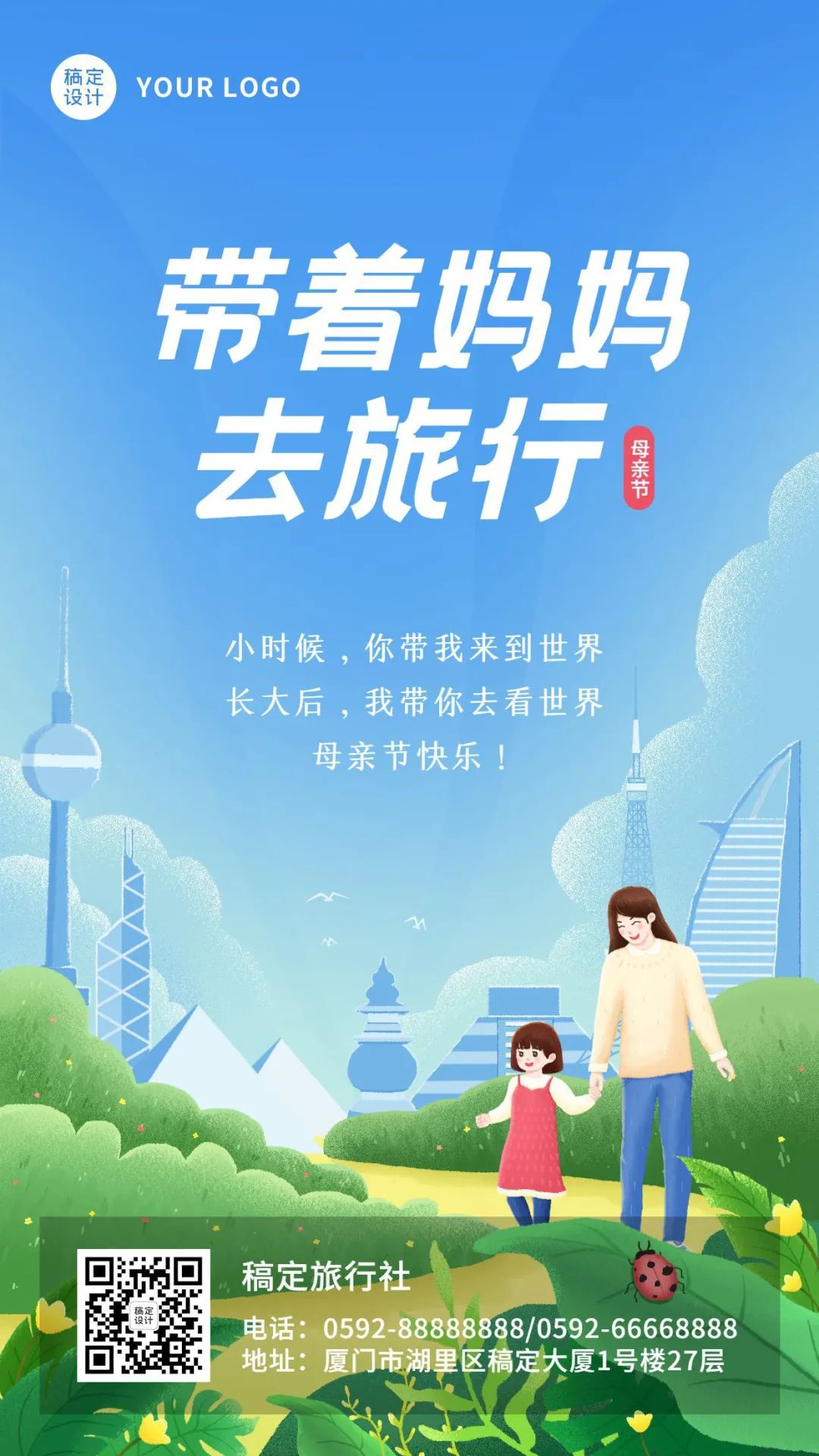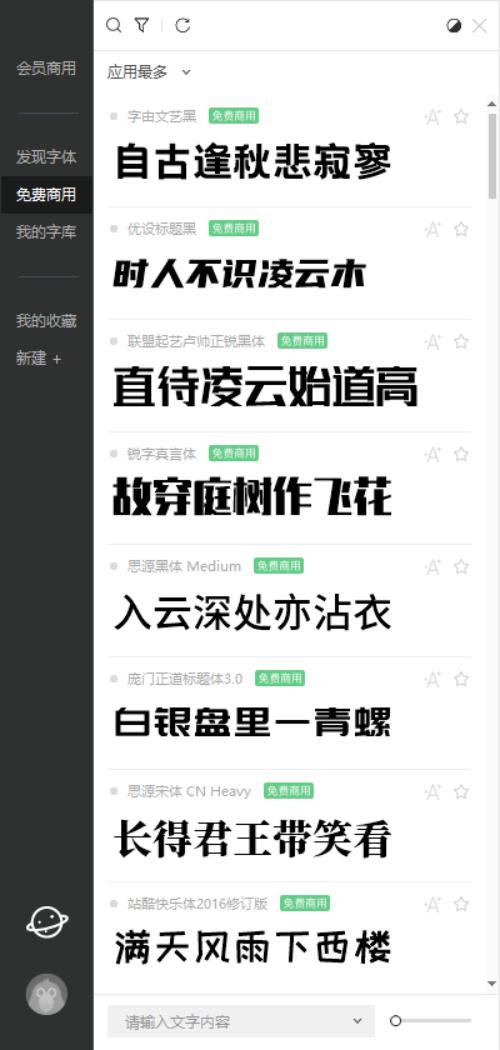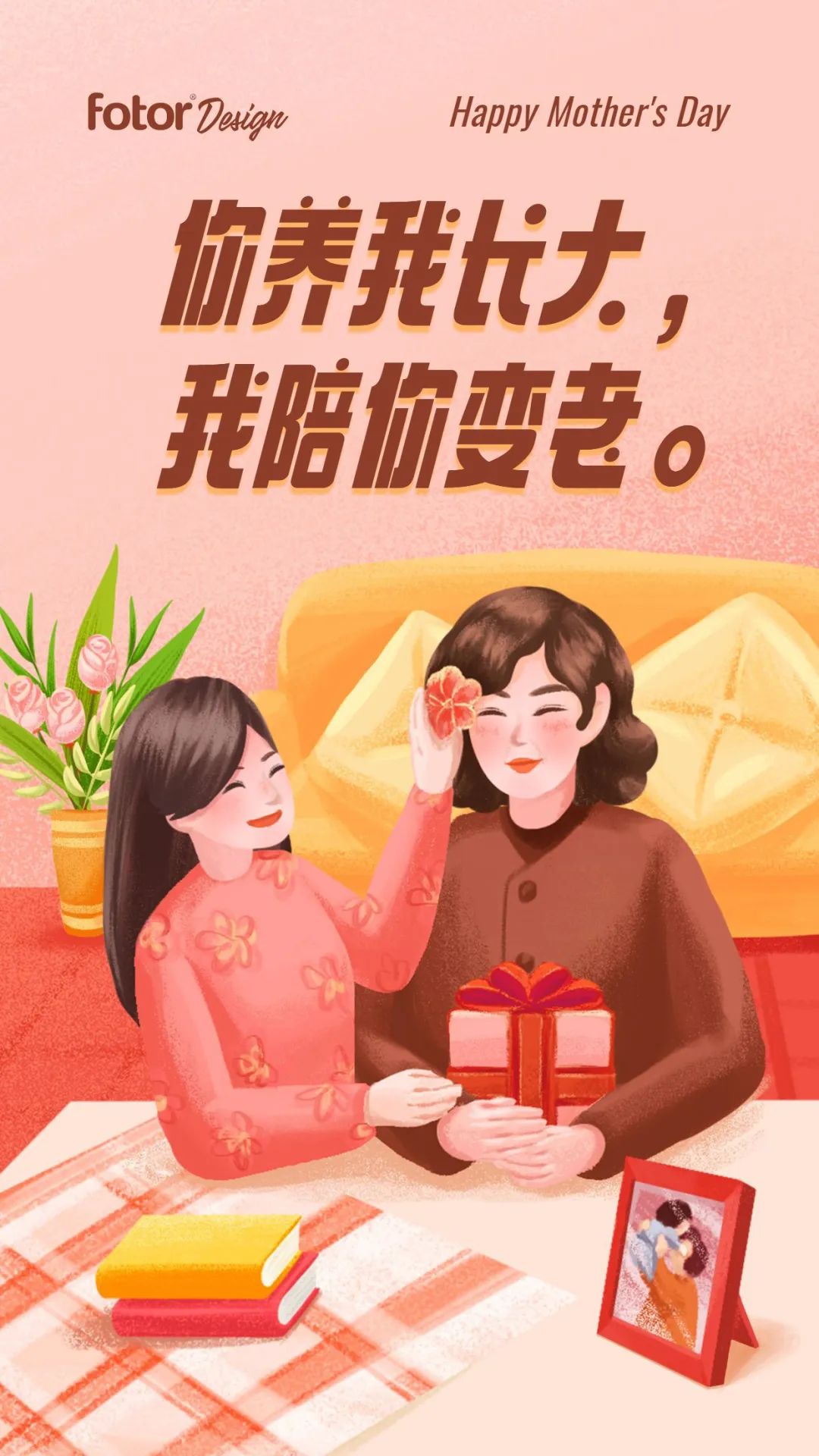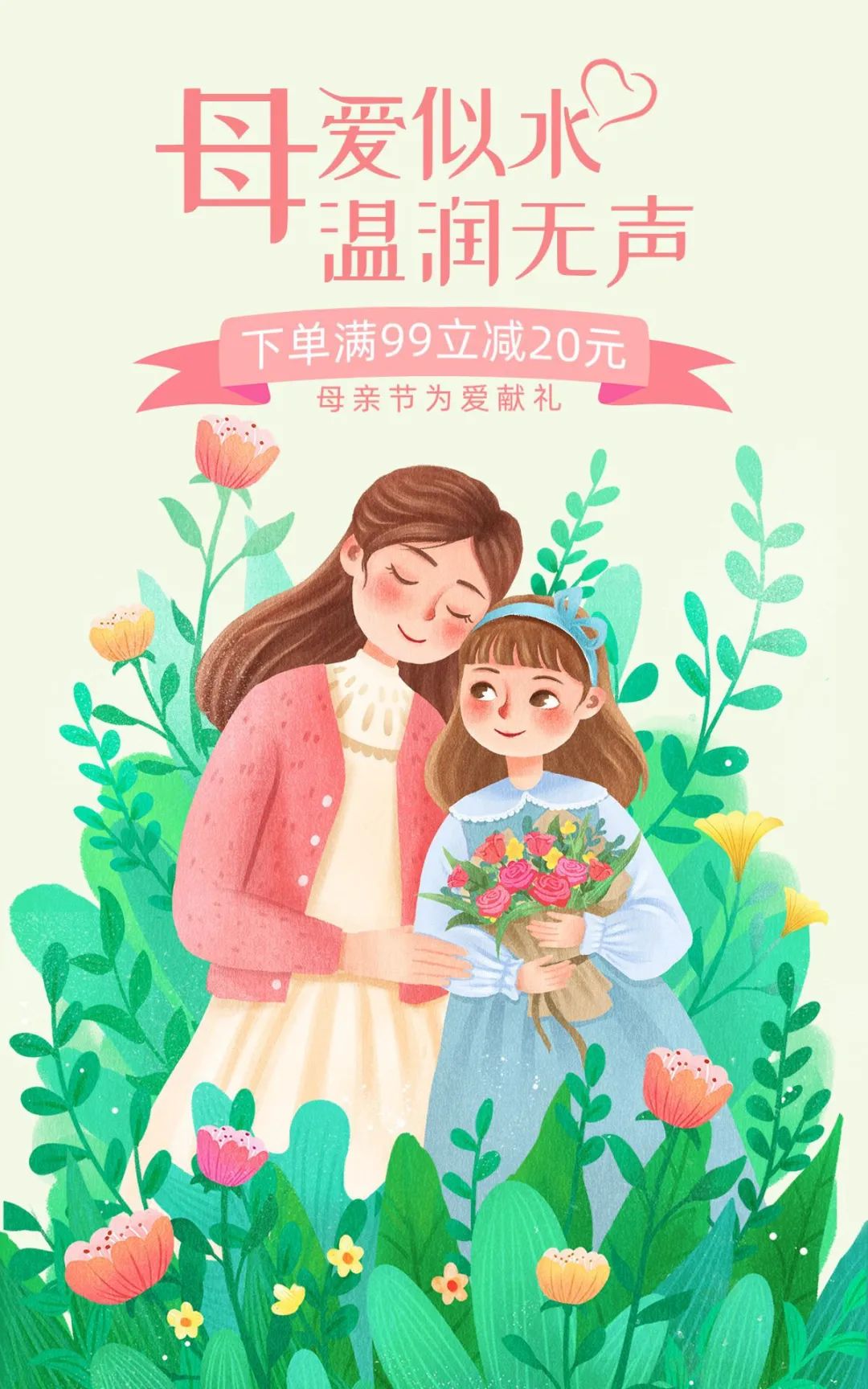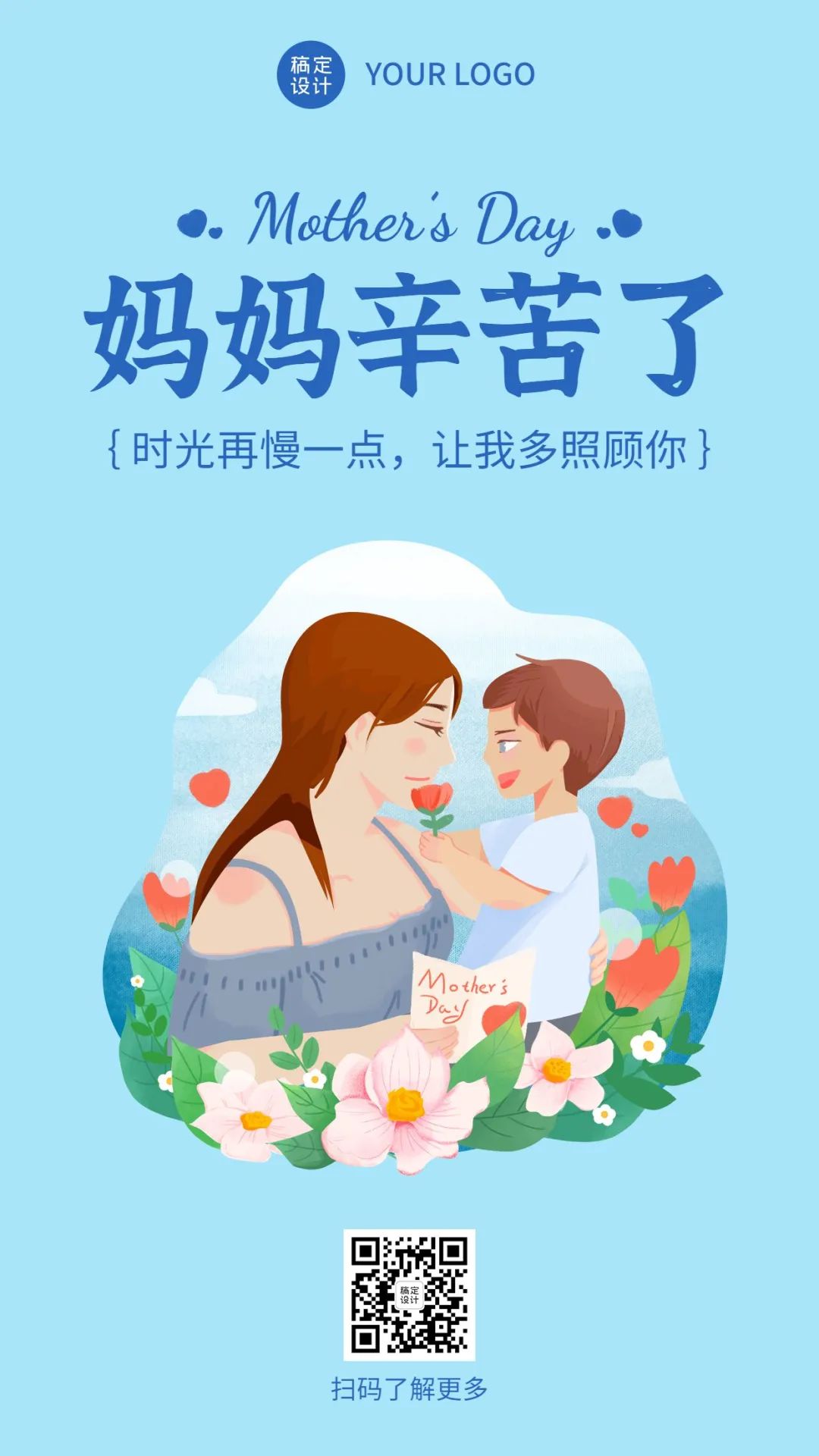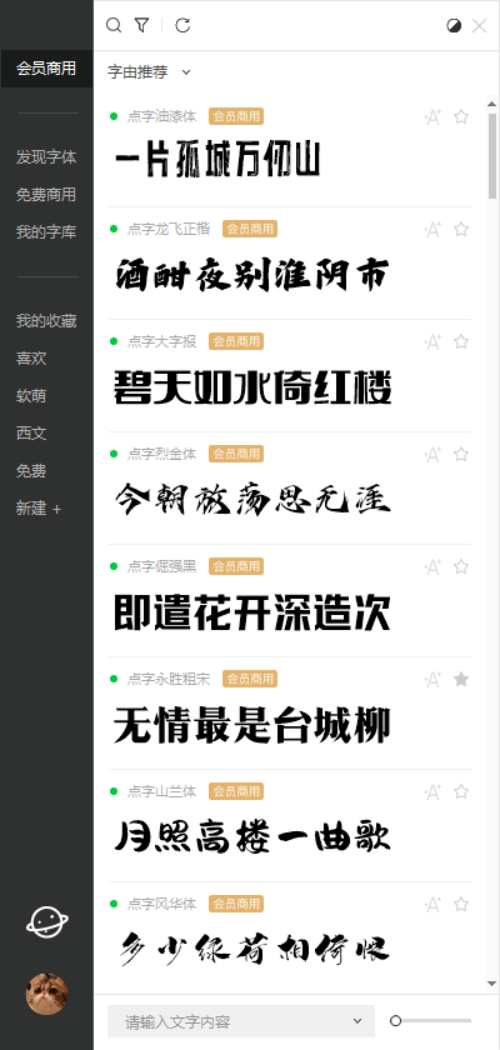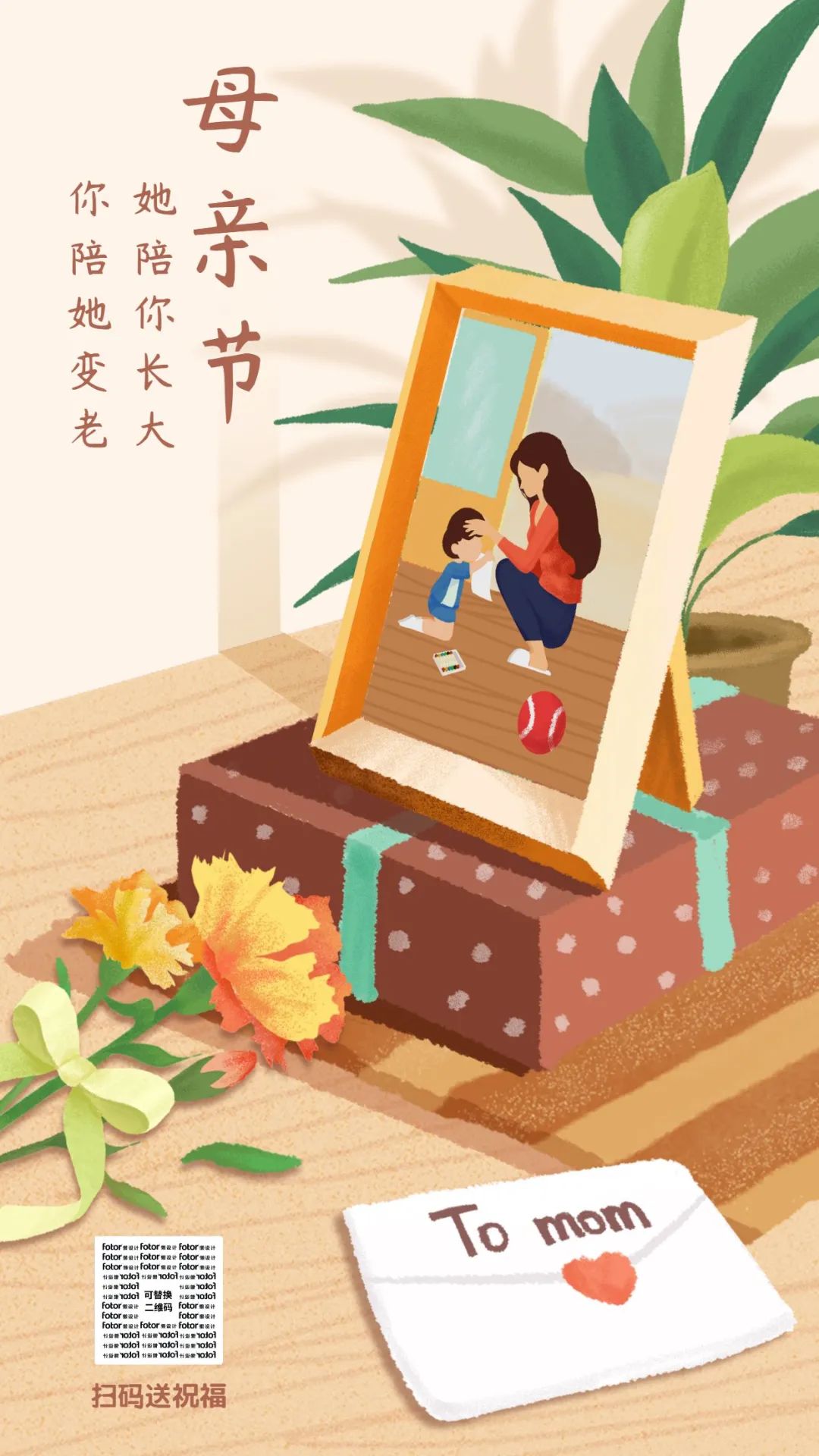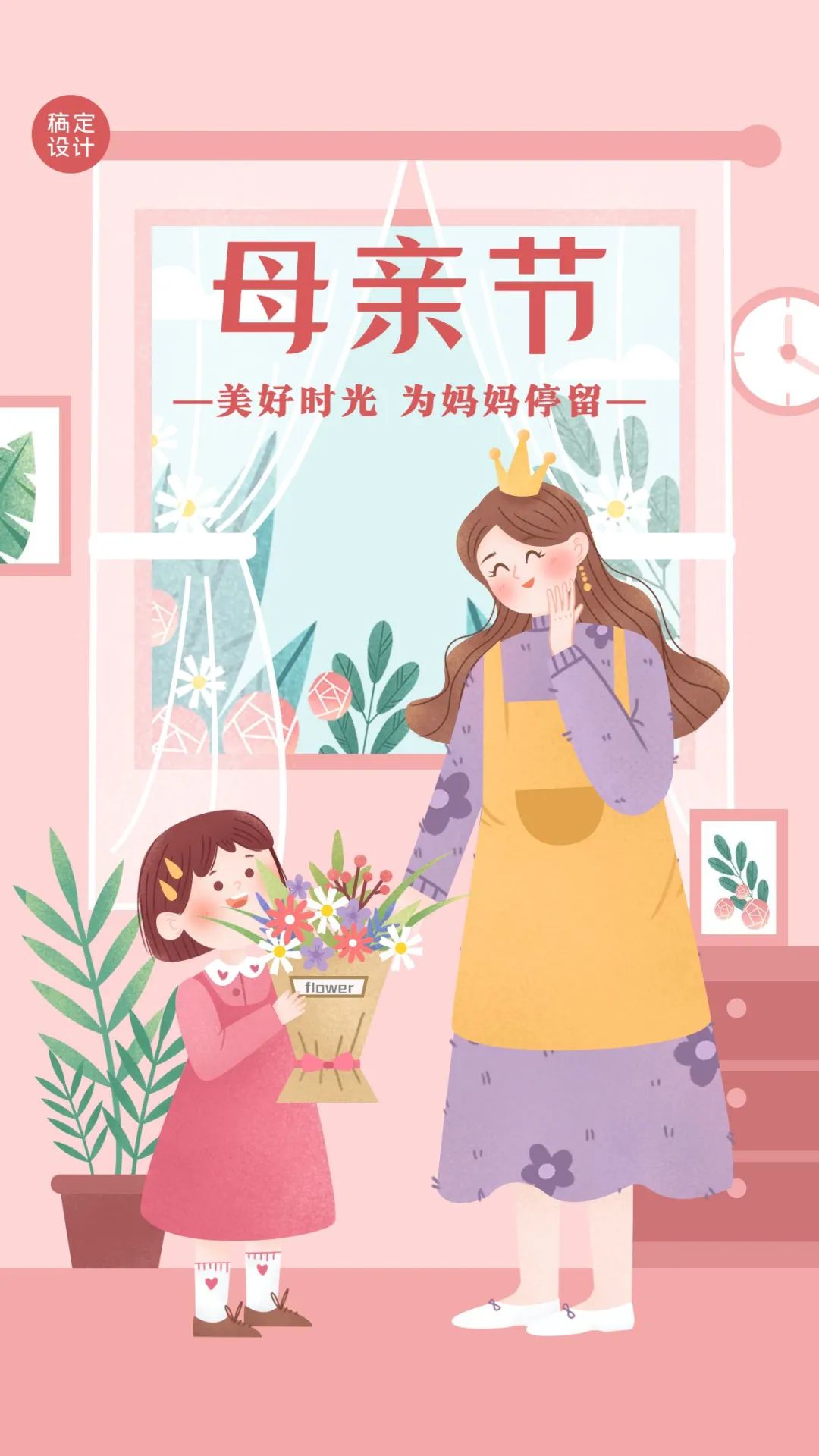
母亲节海报字体推荐,适合母亲节的字体大全
五一小长假过后,你缓过来了吗?没关系,马上就是母亲节了(就是这么秃然)……
其实每年母亲节,柚子都没有缺席,发过相关的字体,比如:
里面有很多适合母亲节主题的字体,比如字由芳华体、字由文艺黑、优设好身体、站酷小薇logo体、江西拙楷、杨任东竹石体等。
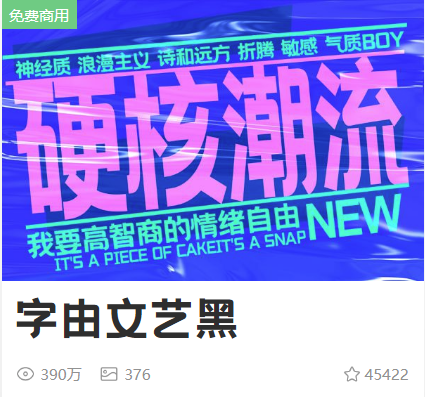
会员字可选择的余地就更大了,不管是优雅的点字美玲体,手写感的点字刻宋,还是浓情的点字逸致体,复古的点字大字报,年代感的点字淡墨行楷,总有一款契合你的主题。